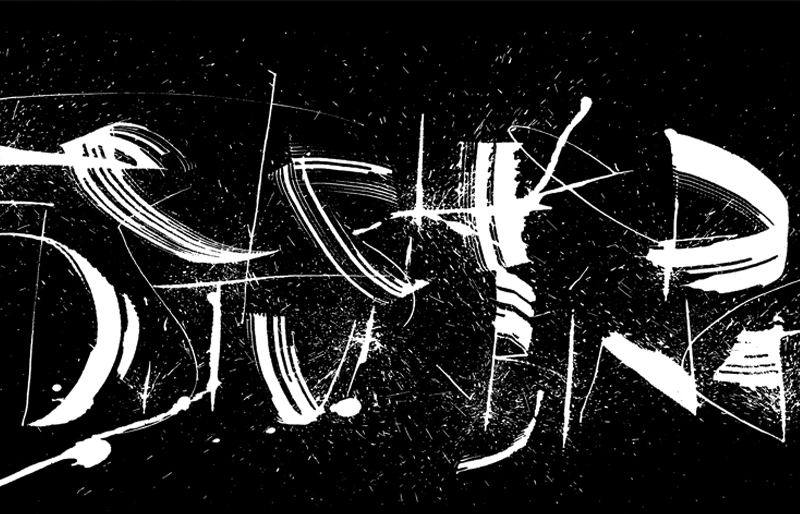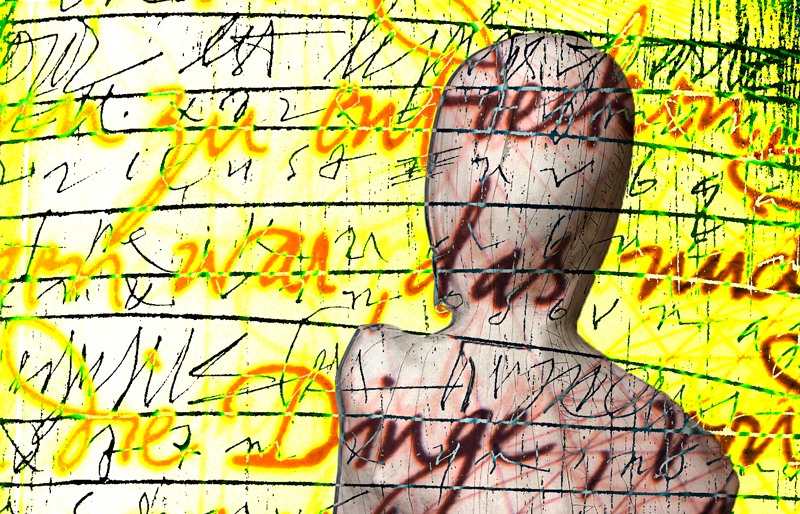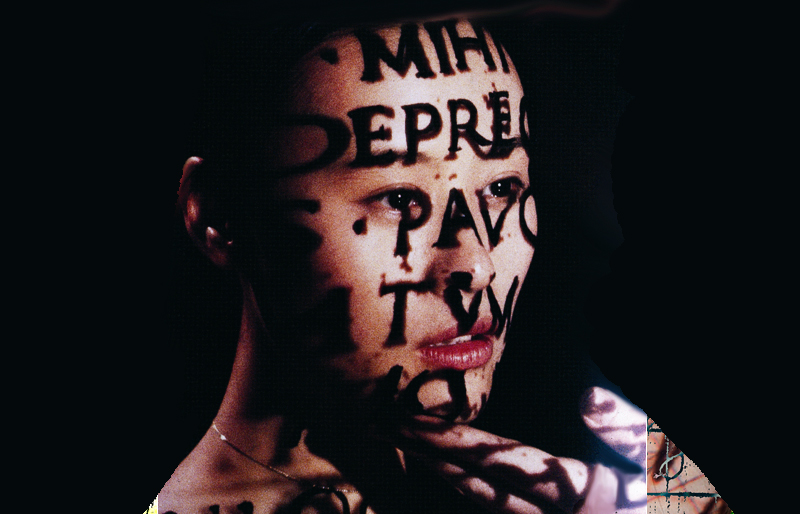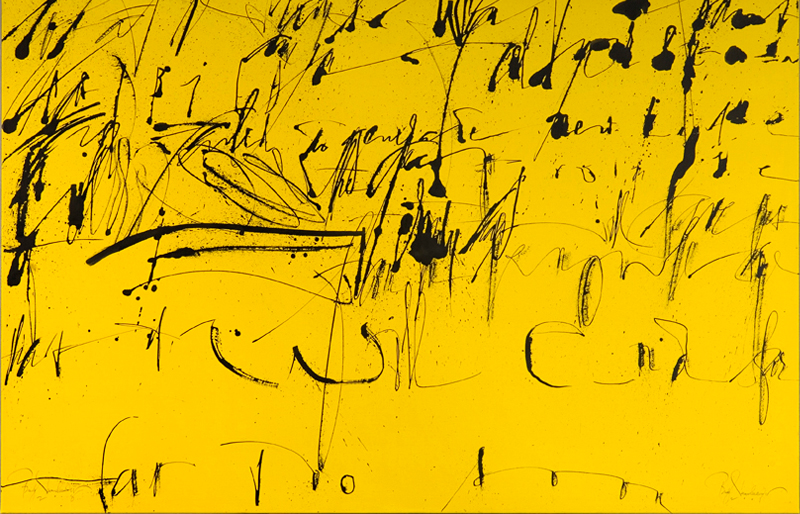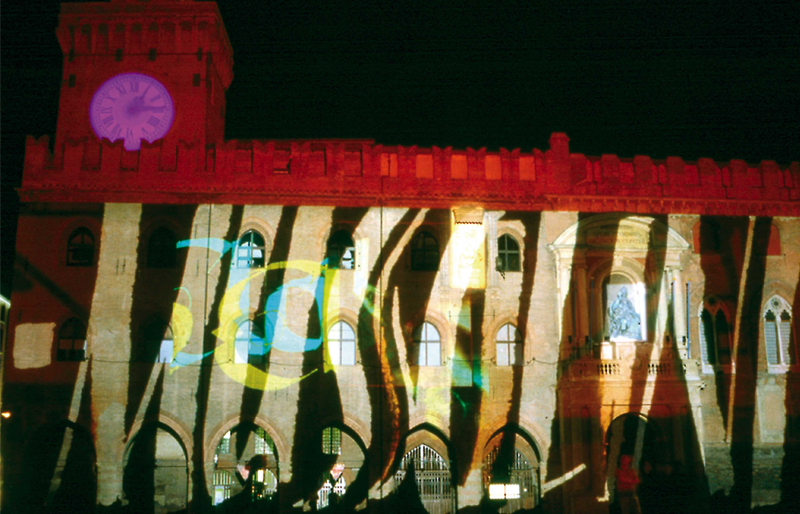
The Calligraphic Line: Expressing Yourself in Letterforms
Geleneksel ve modern araçları kullanarak harfbiçimleri üzerinde denemeler yapmaya ayrılmış altı saatlik bir oturum. Harfbiçimleri grafik tasarımın temel unsurudur. Tasarımcıların çoğu mevcut yazıbiçimleriyle çalışır, grafik kompozisyonlar oluştururken bu yazıbiçimleriyle ekranda oynarlar. Oysa harfbiçimleri aslında kalem ve mürekkep ile yapılan işaretlerdi. Günümüzde el teknikleriyle harflerin grafik, ritmik ve hatta duygusal etkisi üzerine hala sınırsız çeşitleme üretilebilir. El çizimi harfler ile dijital uygulamaların birleştirilmesi yaratıcılığın parlamasına yol açabilir. Bu atölye çalışmasında kalem ve mürekkebin sunduğu fırsatları keşfe çıkacağız. Bir yandan da el çizimi harflerin filmden videoya projeksiyondan enstalasyona yeni medya ile nasıl bir arada kullanılabileceğine bakacağız.